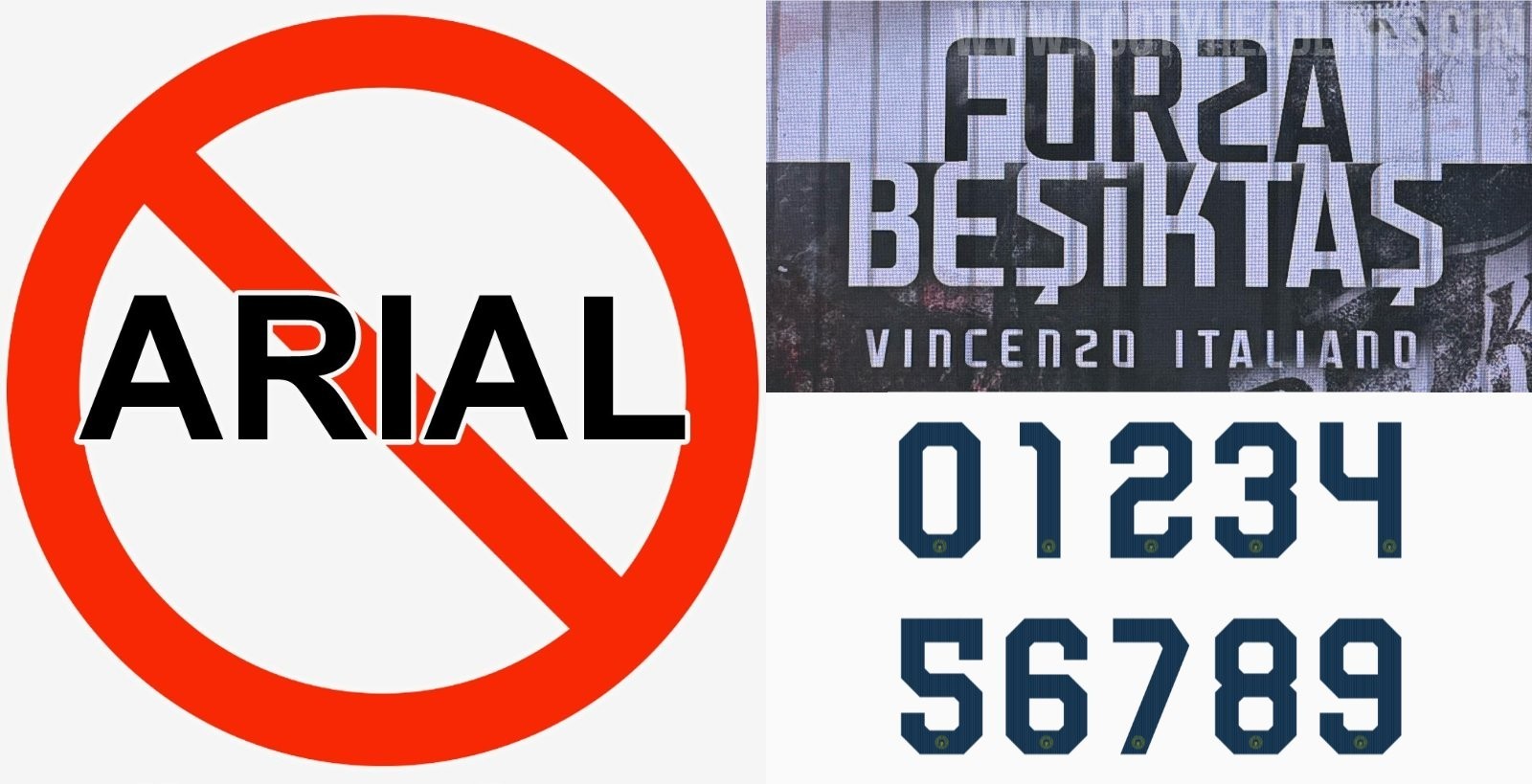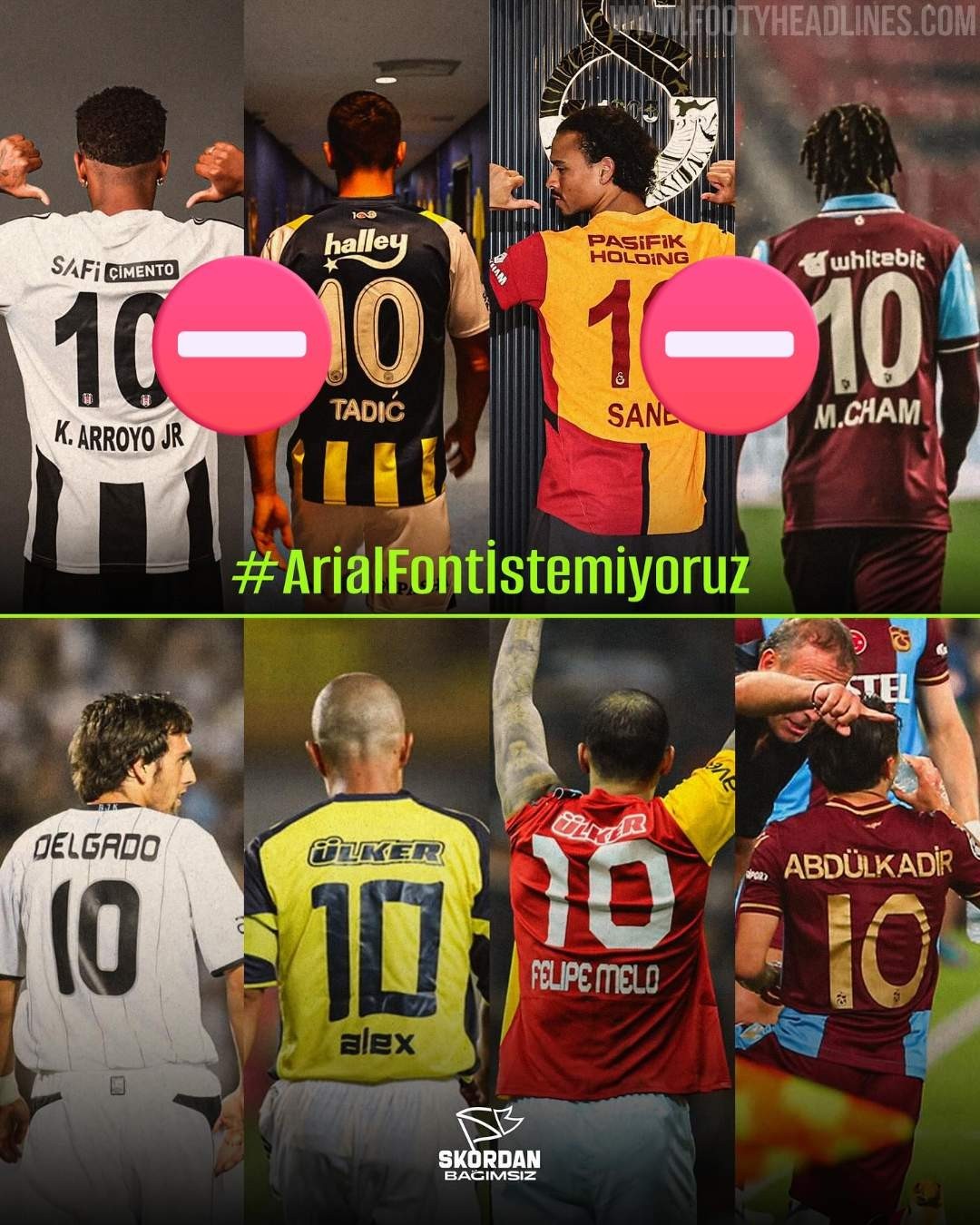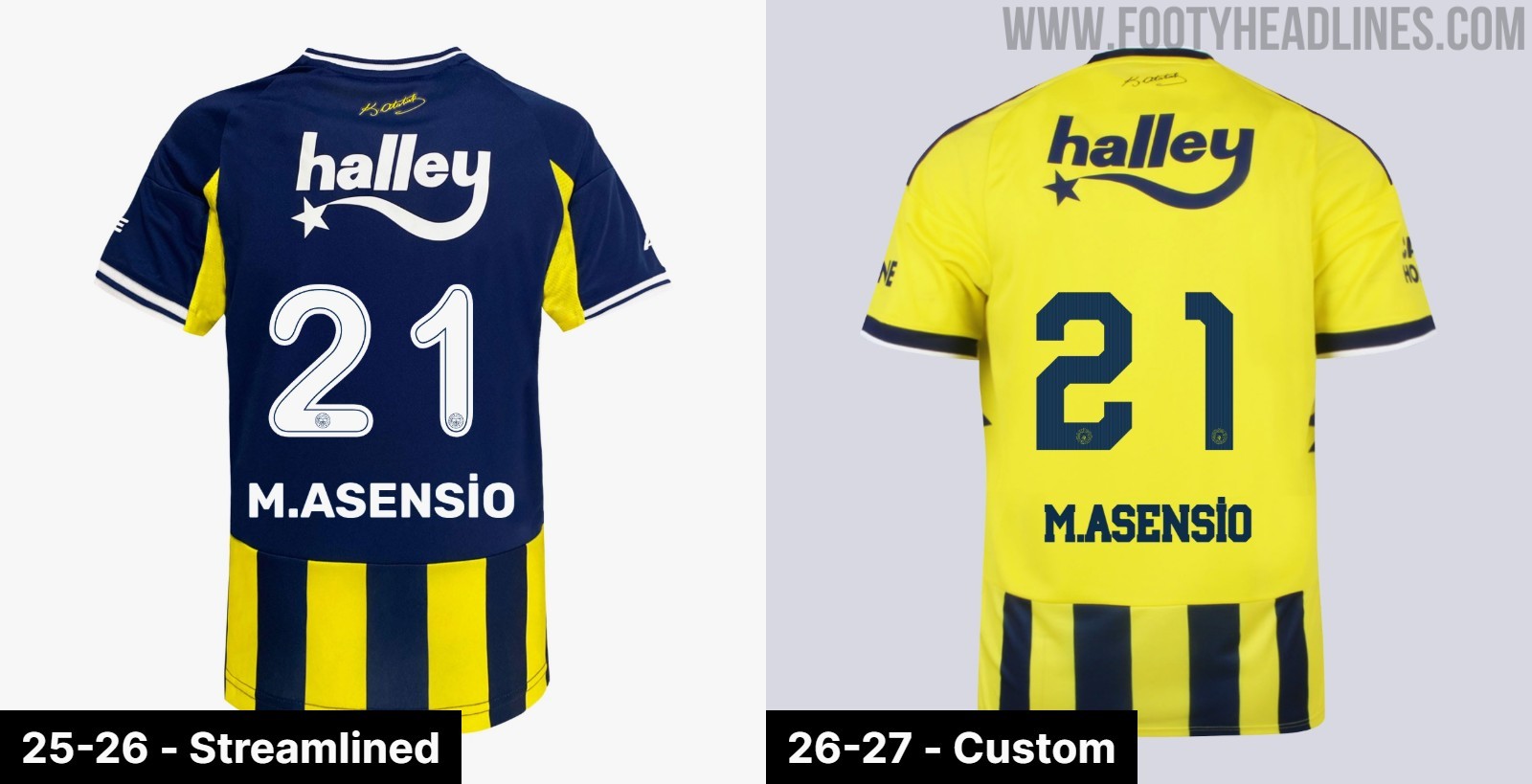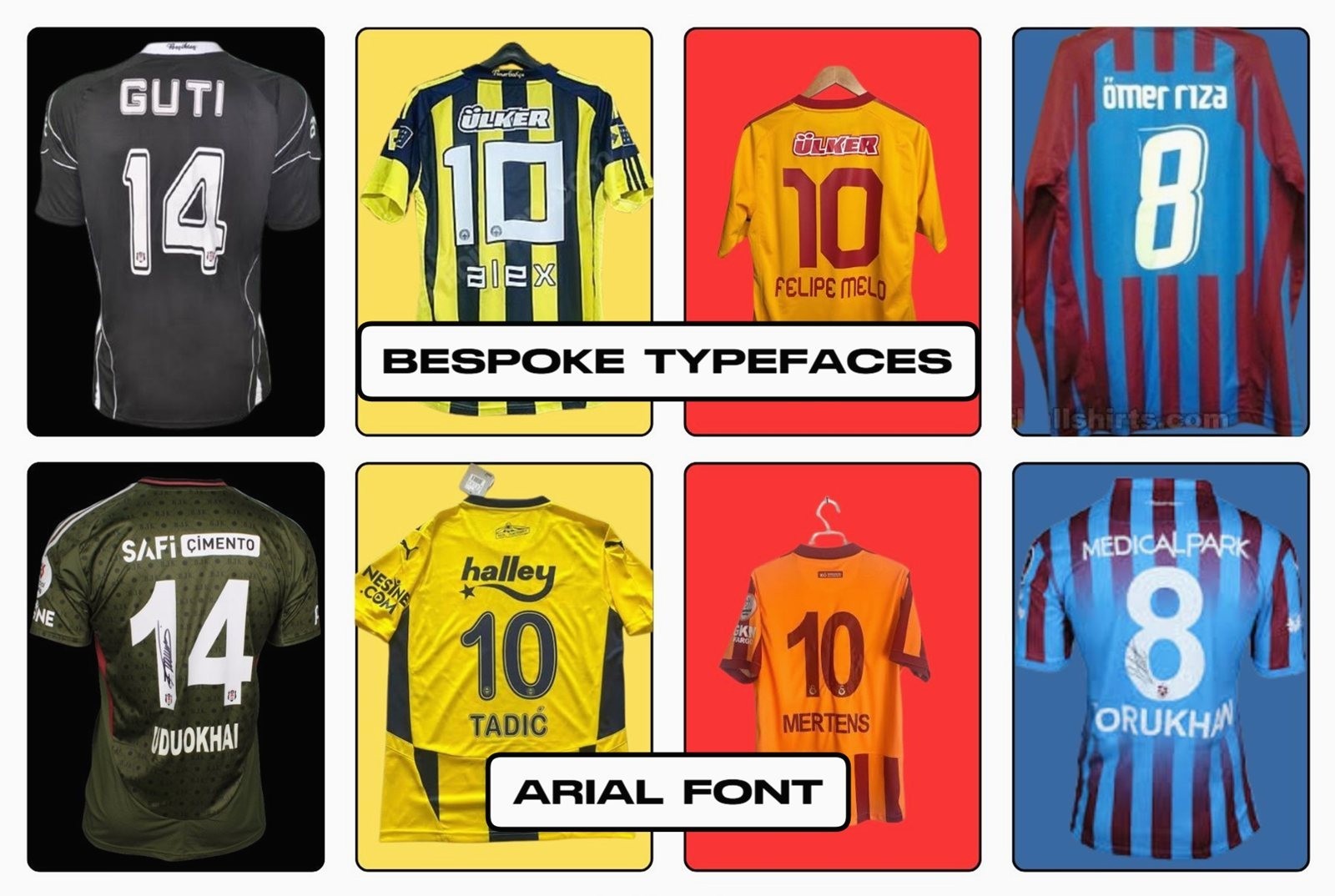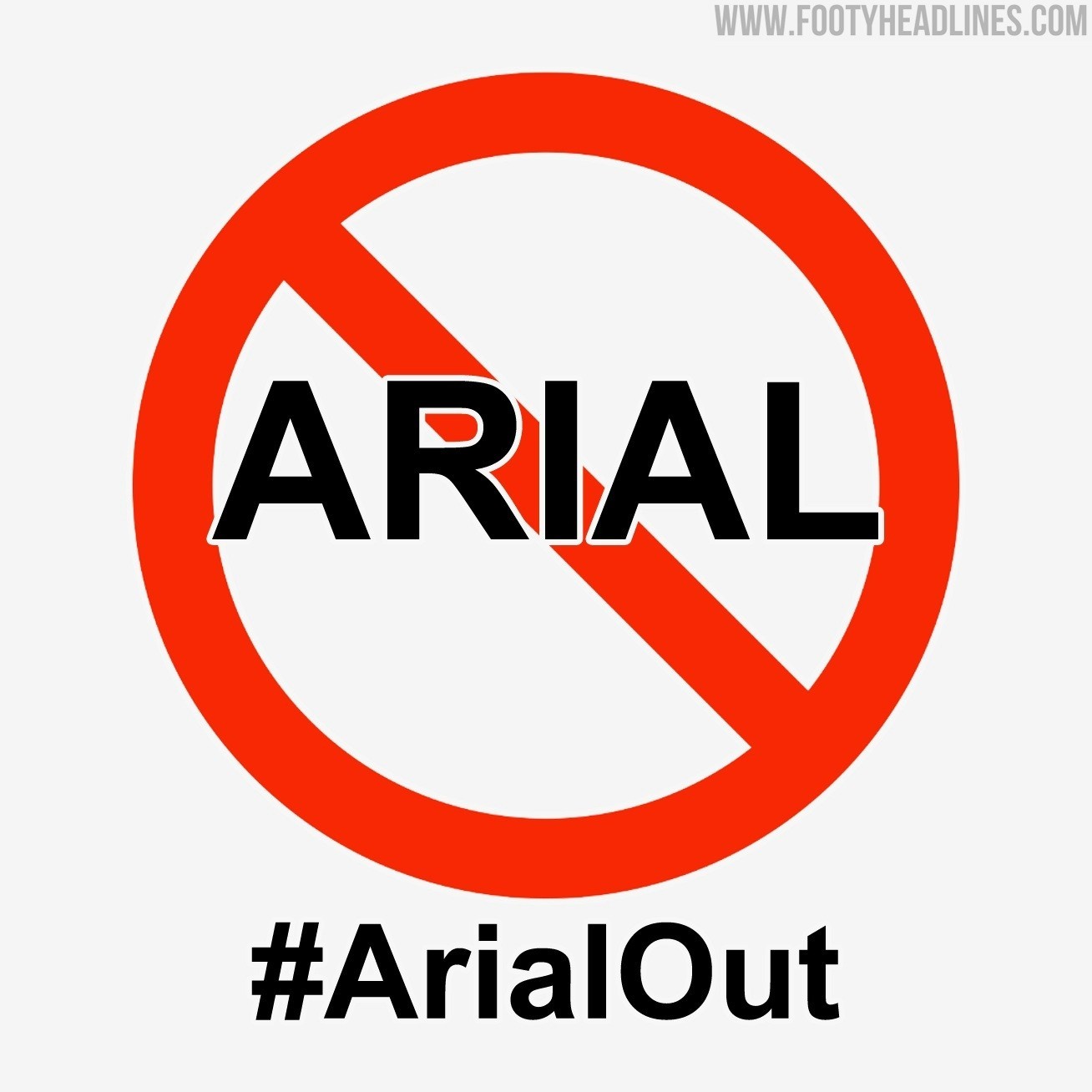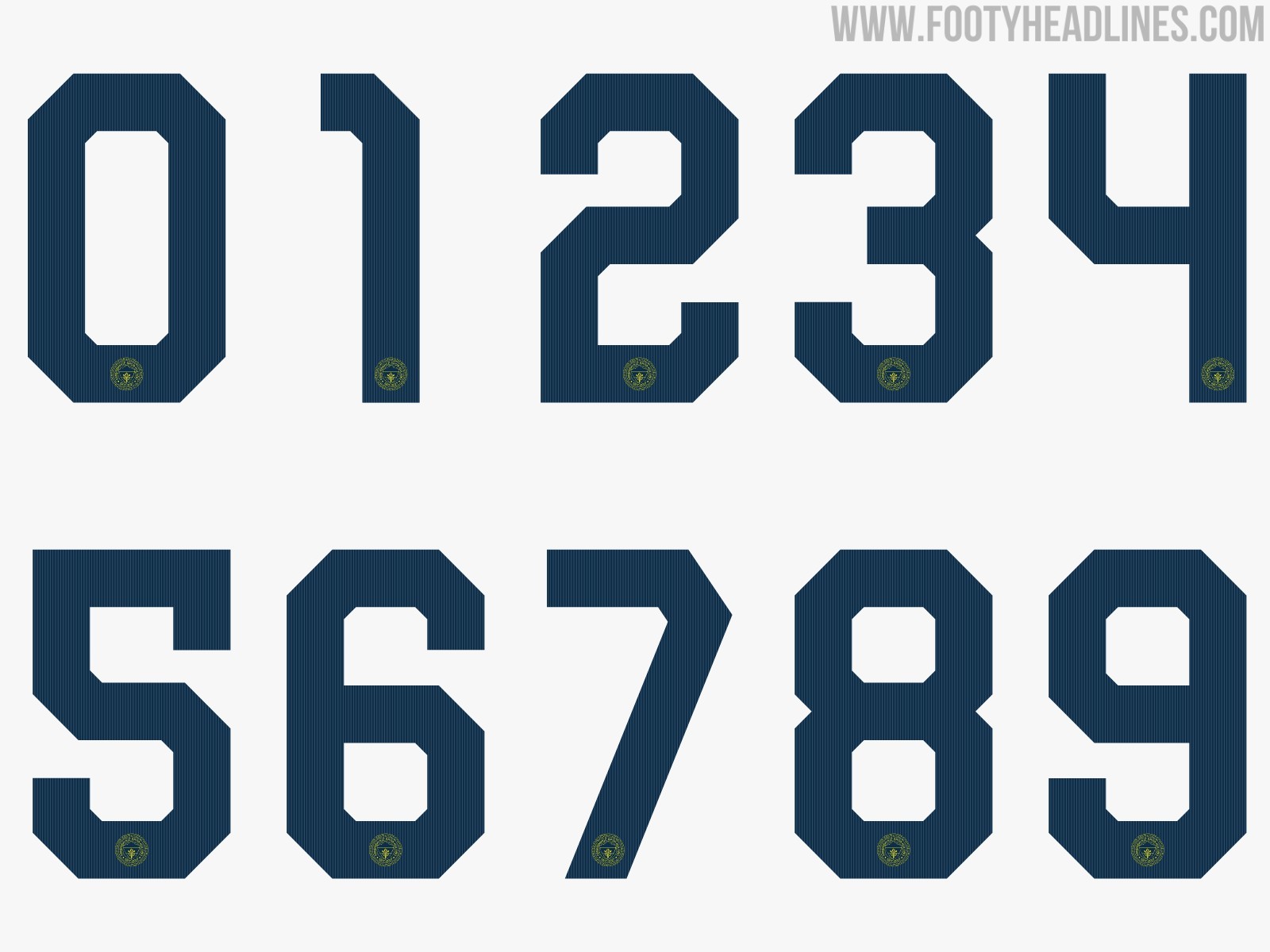
Fine dell'era Arial nella Süper Lig: i club avranno font personalizzati per le maglie nella stagione 2026-2027
• Fine dell'era Arial: Dopo oltre un decennio di frustrazione dei tifosi, la Federazione Turca di Calcio (TFF) ha abolito l'uso obbligatorio del font Arial standardizzato per le maglie della Süper Lig.
• Implementazione dal 2026-27: La decisione di abolire l'uso del font generico è stata formalizzata nel luglio 2025, ma i club potranno implementare i nuovi font personalizzati solo a partire dalla stagione 2026-27.
• Libertà creativa per i club: I club della Süper Lig, come Fenerbahçe, Beşiktaş e Galatasaray, avranno finalmente la libertà di scegliere la propria tipografia personalizzata per le maglie, riflettendo la propria identità visiva.
Da oltre un decennio, i tifosi turchi esprimono la loro frustrazione per un dettaglio apparentemente insignificante, ma di grande impatto, sulle maglie delle loro squadre: la tipografia. Dal 2012, la Federazione Turca di Calcio (TFF) ha imposto una norma rigida che obbliga tutte le squadre della Süper Lig a usare un font Arial standardizzato e generico per i nomi e i numeri dei giocatori. Mentre altri grandi campionati europei hanno continuamente aggiornato la loro identità visiva con caratteri tipografici moderni e personalizzati, la Süper Lig è rimasta bloccata in una routine visiva. Tuttavia, dopo anni di intense proteste dei tifosi e campagne sui social media con hashtag come #ArialOut, l'"era Arial" è ufficialmente finita.
Fine dell'era Arial nella Süper Lig: i club avranno font personalizzati per le maglie nella stagione 2026-2027
La TFF ha formalmente abolito l'uso obbligatorio del font generico nel luglio 2025, garantendo ai club la libertà creativa di scegliere la propria tipografia. Anche se la decisione è arrivata troppo tardi perché i club potessero implementare i cambiamenti per la stagione 2025-26 – dato che i disegni delle maglie e le produzioni erano già stati finalizzati mesi prima – l'impatto di questa decisione storica si concretizzerà pienamente nella prossima stagione 2026-27.
Cosa aspettarsi nel 2026-27
Mentre le squadre si preparano per la stagione 2026-27, che prenderà il via a metà agosto, cresce l'attesa per vedere come i club sfrutteranno questa nuova libertà creativa.
• Fenerbahçe: I giganti di Istanbul sono stati tra i primi ad affrontare il cambiamento di regolamento. In seguito all'annuncio della TFF dello scorso anno, il Fenerbahçe ha rilasciato una dichiarazione in cui riconosceva il feedback dei tifosi e affermava esplicitamente che stavano "valutando questo feedback per rifletterlo sulle nostre maglie per la prossima stagione". Il club ha un font personalizzato per le maglie Adidas 2026-2027
• Beşiktaş: Le Aquile Nere stanno entrando in una nuova era su più fronti. Non solo debutteranno con un nuovo font, ma la stagione 2026-27 segna l’inizio della loro nuova partnership per le maglie con Nike, dopo aver lasciato Adidas.
• Galatasaray: Anche se i dettagli specifici sulla scelta dei font del Galatasaray non sono ancora stati rivelati ufficialmente, i campioni in carica sfrutteranno sicuramente l’occasione per avere delle maglie con un design personalizzato che rifletta il loro marchio iconico.
L'abbandono del font Arial è una grande vittoria per la cultura calcistica turca. Il generico font Arial era stato ampiamente criticato dai tifosi e appariva decisamente poco originale rispetto alla tipografia personalizzata che si vede in Premier League, La Liga o Serie A. Ora, cosa ancora migliore per i club, hanno un proprio carattere tipografico.